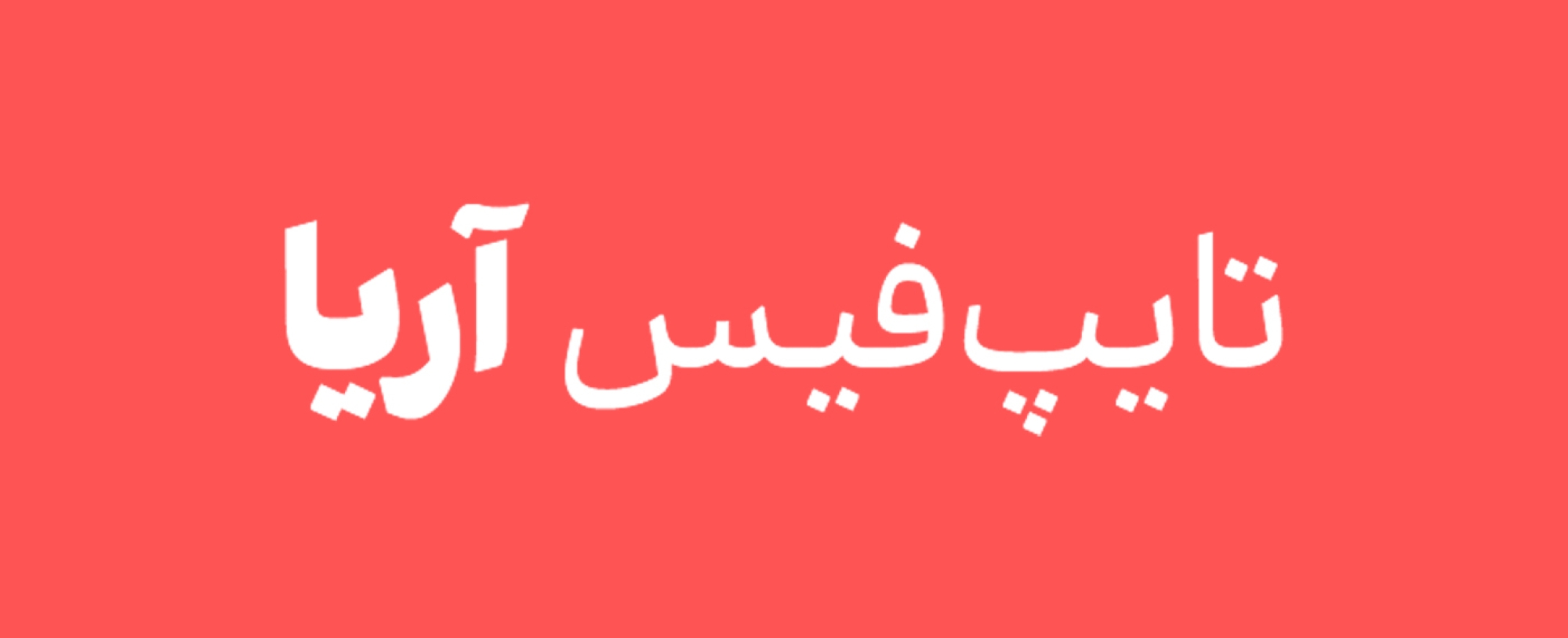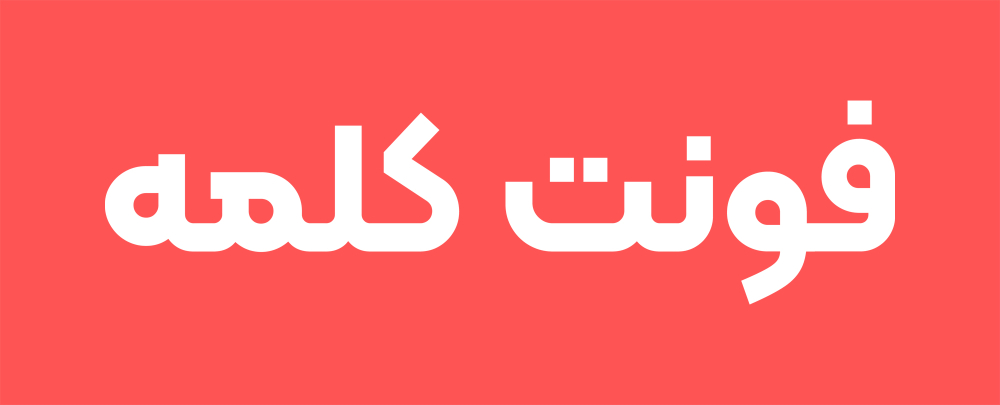
فونت آریا یک خانواده فونت کامل به سبک نسخ معاصر است که دارای ترکیبات، حروف جایگزین و امکانات متعدد اپنتایپ و فونت متغیر است.
اگر بخواهیم بدون جانبداری و تعریفهای رایج صحبت کنیم بایستی بگوییم که همکاری، زیباترین نتیجهی این تایپفیس است. اینکه دو طراح از دو نسل متفاوت در زمان قرنطینه بدون اینکه حتی یکبار با هم ملاقات داشته باشند، بتوانند با هم کار کنند و به زبان مشترک در دیزاین یک تایپفیس دست پیدا کنند.
فرم حروف و اسکلت کار برگرفته از خط نسخ است. اما در مورد کاربرد، تلاش ما بر این بود که در هر دو رسانه (وب و پرینت) نتیجهی قابل قبولی داشته باشد و از تمام زبانهای خط (script) عربی پشتیبانی کند.
هرکدام از وزنها را با توجه به استفاده و کاربرد همان وزن بازسازی کرده و حروف مرکب و جایگزین کاملی را طراحی کردیم.
در کنار همهی اینها «آریا» وریبلفونت هم دارد تا دست کاربر در استفاده از آن کاملاً باز باشد و هیچ کمبودی احساس نکند.
سعی ما بر این بود که روشهای استاندارد طراحی و ساخت فونت را با هم داشته باشیم تا مخاطب از این به بعد، به کمتر از این استانداردها عادت نکند.
فونت آریا از زمستان ۱۳۹۹ شروع و در پاییز ۱۴۰۰ به پایان رسید. این فونت، پروژه مشترک امید امامیان و کامیاب جعفری است.
فونت کلمه، ساختاری هندسی و منظم دارد. استخوانبندیِ اندامِ این قلم به شما فضایی شسته و رفته ارائه میدهد.
پویایی و انرژیِ فونت کلمه ، برای استفاده در اکثر آثار تبلیغاتی بهویژه برای استارتاپها و کسبوکارهای خلاق و نوین بسیار مناسب است.
فونت کلمه، قدرتمند و خودنماست؛ در متنهایی که تلاش دارند ویژگیها و تواناییهای خاصی را برجسته کنند و نکاتِ طلاییِ موضوع را شاخص نمایند، “کلمه” این قدرت را به آنها میدهد.
تایپفیس “کلمه” برای زبان فارسی، عربی و انگلیسی طراحی شده است و از زبانهای اردو و کردی نیز پشتیبانی میکند.
نسخه چهارم خانواده فونت کلمه، با اصلاحاتی نسبت به نسخههای پیشین و اضافه کردن حالتهای جایگزین حروف و پشتیبانی از زبانهای جدید ارایه شده است.
فونت جوان یک فونت دست نویس از نوع نمایشی است. مناسب عنوانهایی که میخواهید پر تحرک، پر نشاط و سرشار از شور جوانی باشد. قاسم نجاری طراح فونت جوان متخصص ساخت چنین فونتهایی است. وی پیش از این فونت آوینی و فونت کتیبه را در وبسایت فونتایران منتشر کرده بود که هر دو فونت از فونتهای بسیار پرطرفدار و پرفروش هستند.
ویژگی اصلی فونت جوان که آن را از دو فونت آوینی و کتیبه متمایز میکند قلم ماژیکی استفاده شده است. فونت جوان از دستخطهای نوشته شده با ماژیک در بعضی آثار گرافیکی و امضاهای گرافیتی الهام گرفته شده است.
فونت جوان دارای تعداد بسیار زیادی حروف و ترکیبات جایگزین است که به کمک راهنمای آن میتوانید آنها را تایپ کنید و به تایپوگرافی دلخواه خودتان دست پیدا کنید. استفاده مناسب از این حروف و ترکیبات جایگزین و ایجاد ترکیب بندی با حروف تا حد زیادی میتواند کار شما را شخصی کند.
فونت ۸۹۸ استنسیل فونتی است نمایشی، که بهترین کارایی آن در عبارتهای کوتاه است.
فونت ۸۹۸ استنسیل خوشنویسانه است، از آن رو که از یک ضخامت واحد در طراحی کارکترها استفاده نشده، و به کمک زوایای مختلف قلم اجزای کارکترها در ضخامتهای مختلف طراحی شده است؛ و بهوضوح وامدار خطوط گذشته بهویژه نسخ است.
فونت ایران سنس پرطرفدارترین فونت فارسی در سالهای اخیر بوده است.
کافه بازار ، دیوار، آپارات ، اسنپ و صدها وب سایت و اپلیکیشن برتر ایرانی از ایران سنس استفاده میکنند.